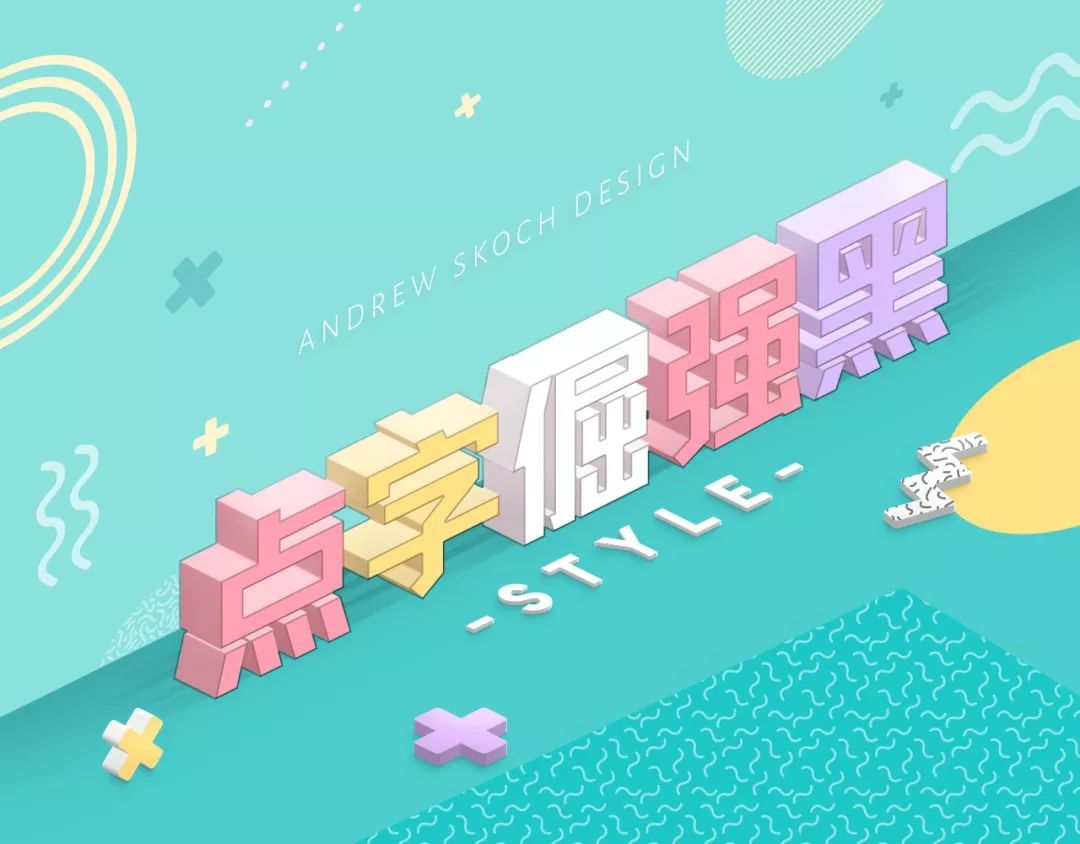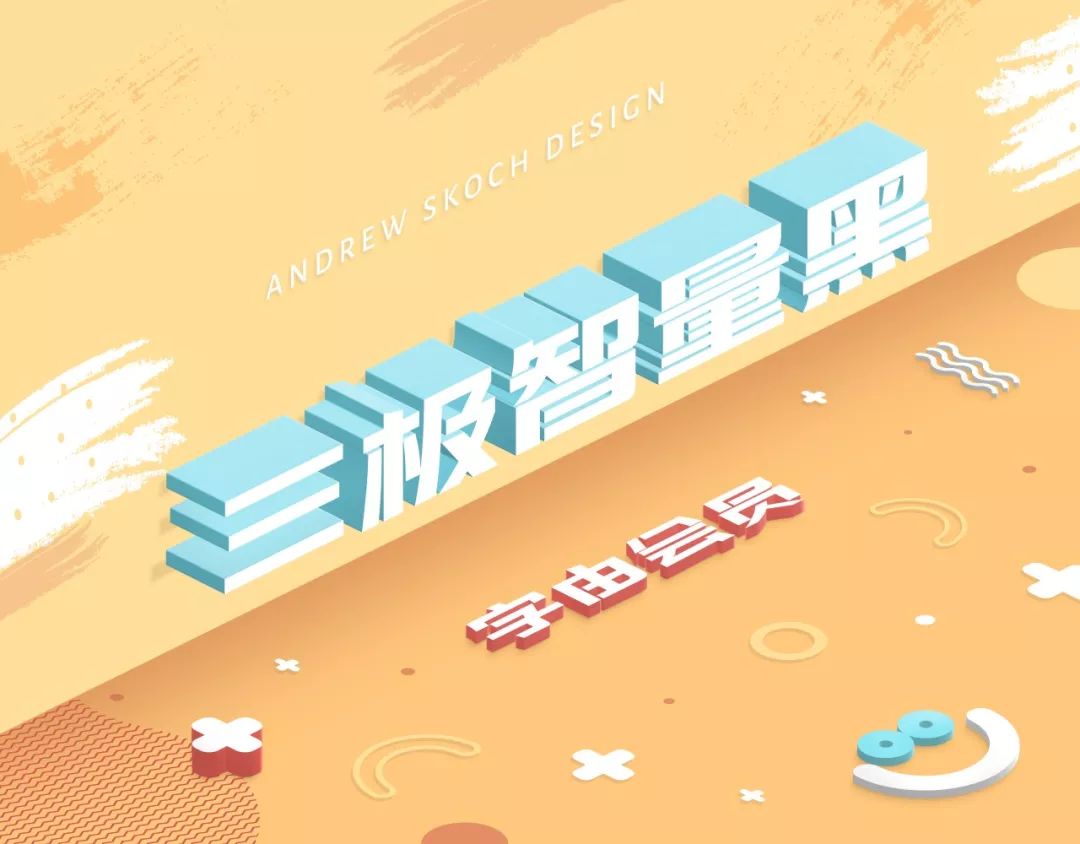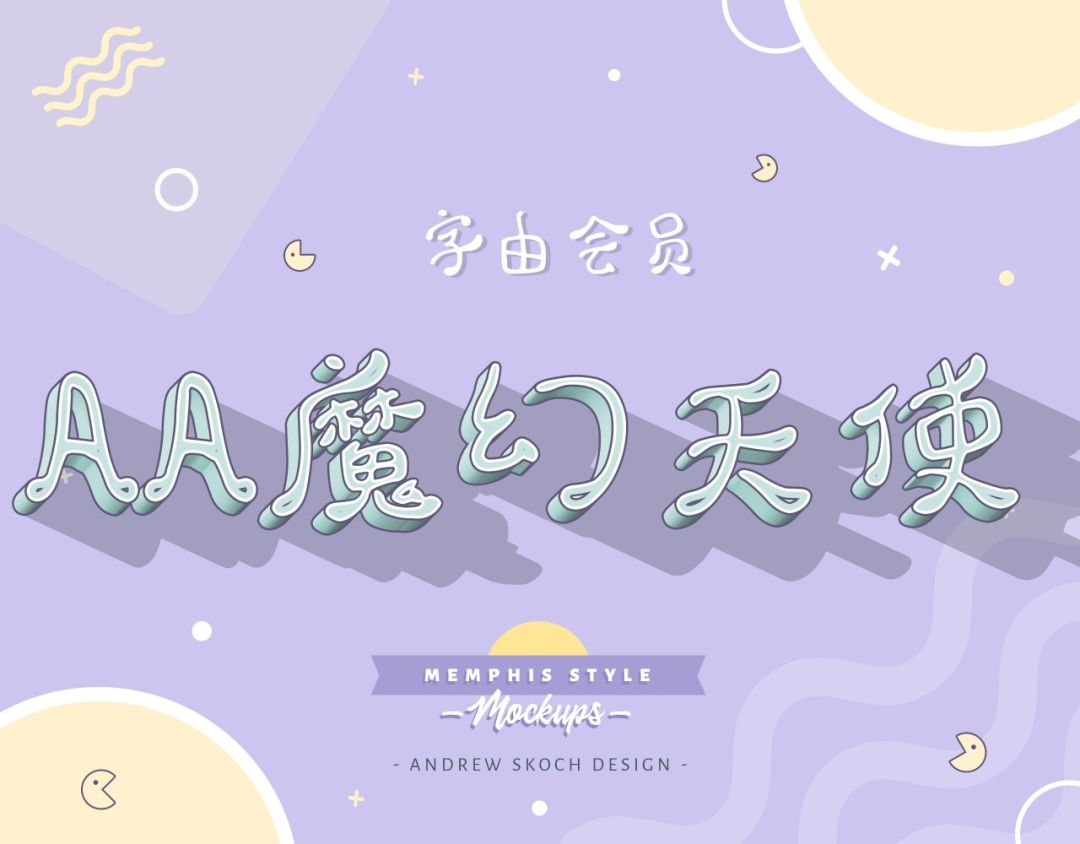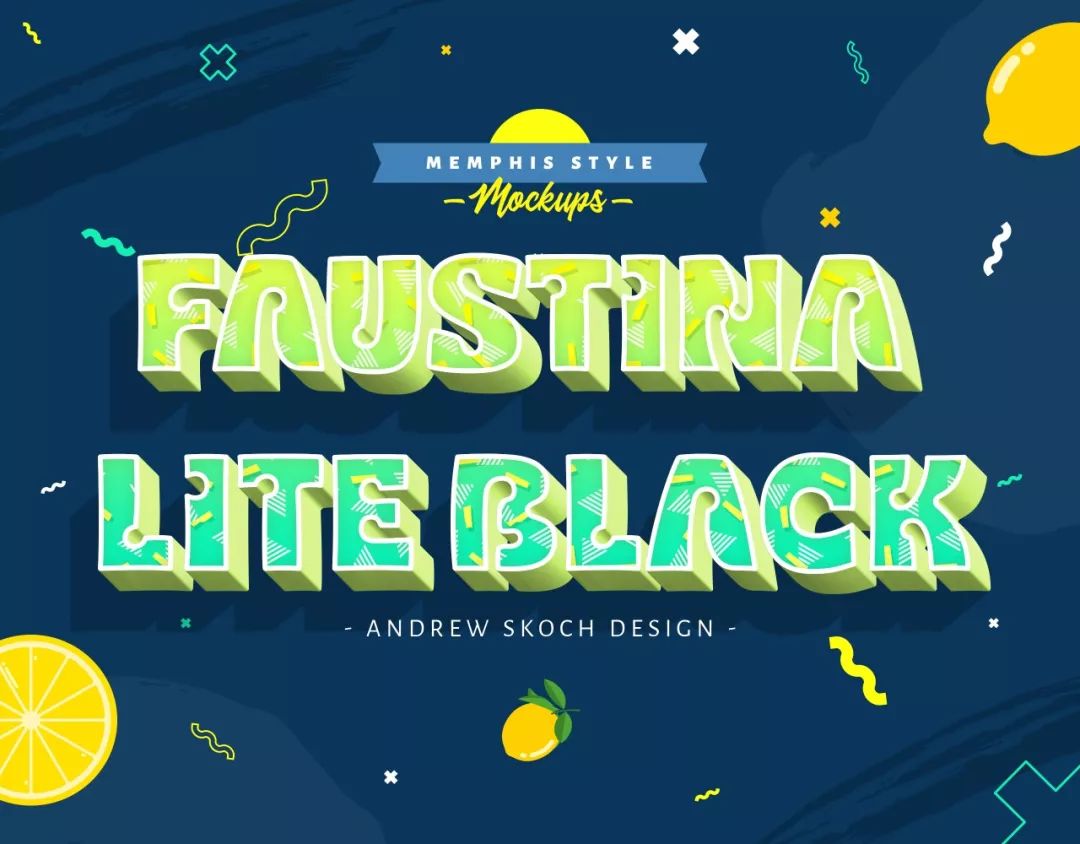
难搞定的孟菲斯又来了,孟菲斯特效福利分享
之前柚子发过一篇孟菲斯不好驾驭?那就手把手教你用AI做一个~阅读量至今名列前茅!
今天继续姐妹篇,不过不用费心学教程了,直接是特效包,哈哈哈~
最近刚上的点字倔强黑表现抢眼,硬朗又有冲击力!
可当它遇到孟菲斯,却有点小清新,爱了爱了~
有点个性又有点可爱的Aa魔幻天使
最适合这种梦幻的感觉~
那小身材大能量的三极智量黑呢?
当然是“变形金刚”更好看~
电商最爱的标题字——阿里汉仪智能黑体
一秒变文气了有木有~
会员最爱的一款西文——Faustina Lite Black
超喜欢这款特效~